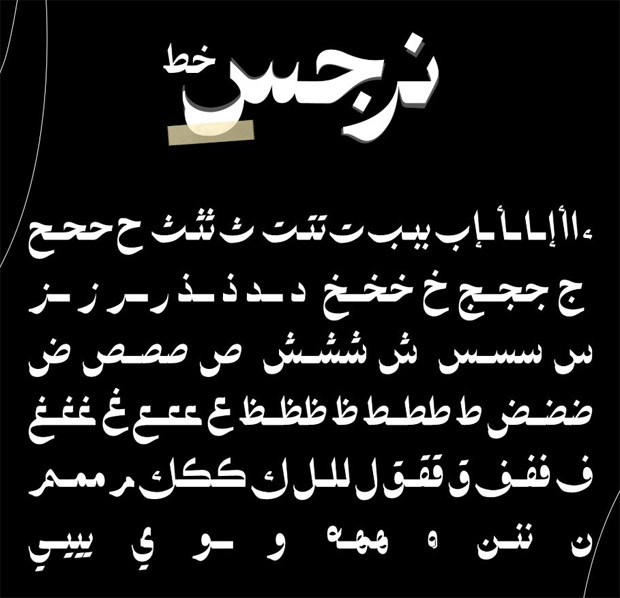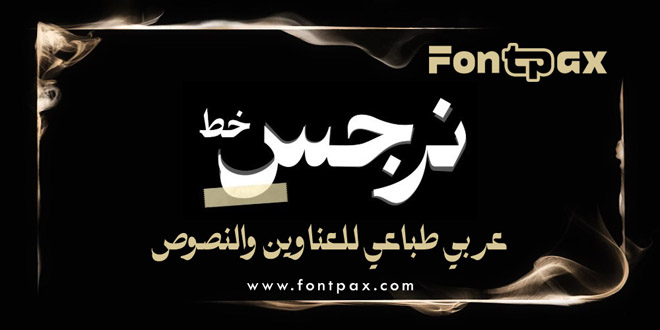
خط نرجس عربي طباعي للعناوين والنصوص .. خط جميل يمتاز بوضوحه وسماكة الخط يمكن استخدامه في كافة أنواع التصميم والعناوين الرئيسية والنصوص واللوحات الدعائية والإعلانية، وهو متاح لللتحميلل المجاني الان.